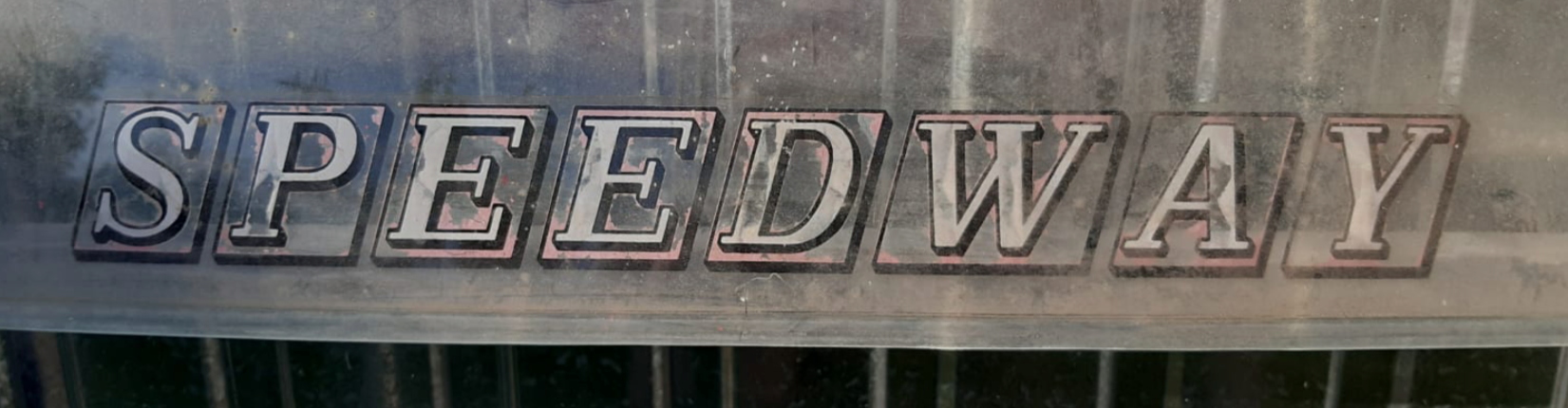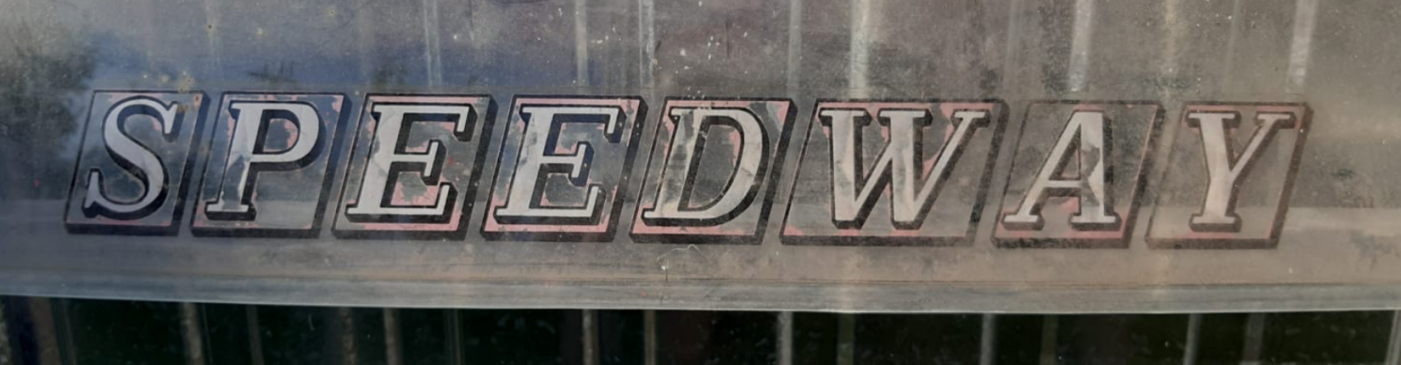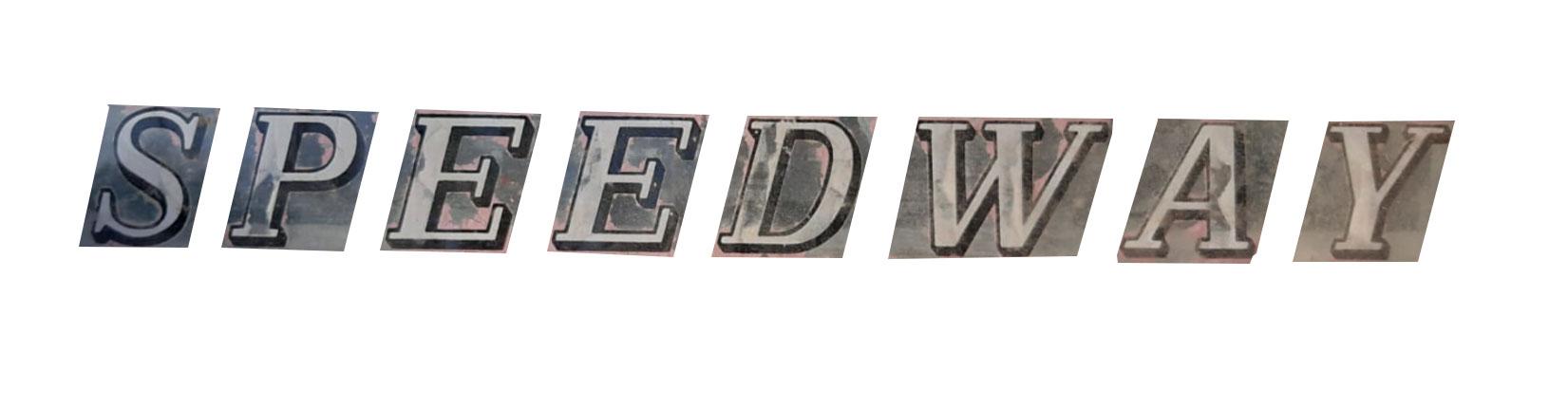
Suche Schrift aus den 70ern? SPEEDWAY Aufkleber
ich suche die schrift zu diesem Siebdruck-Aufkleber. Ich habe schon einige Fachleute gefragt, und bin selbst auf der Suche (What the Font..., usw) habe aber noch kein Ergebnis gefunden.
Leider habe ich auch kein besseres Foto. Auf den ersten Blick könnte es eine EGYPTIENNE sein, ist es aber nicht.
Es könnte auch sein, dass die Schrift gezeichnet wurde. Ich weiß, dass der Aufkleber nicht in Deutschland produziert wurde, sondern eher im Ostblock - Polen - Tschechien usw...
Ich würde mich echt wahnsinnig freuen, wenn hier jemand ne Idee hat, oder zumindest eine Schrift sagen kann, die ich evtl. mit wenig Kopfschmerzen umbauen könnte.
Im Grunde kann man sagen, alles,as eta älter als 40 Jahre ist, und nicht mit Druckerschwärze auf Papier gedruckt wurde, hatte praktisch keinen Zugang auf irgensie benannte Schriftarten, und ist so in den allermeisten Fälle von Hand gezeichnet.